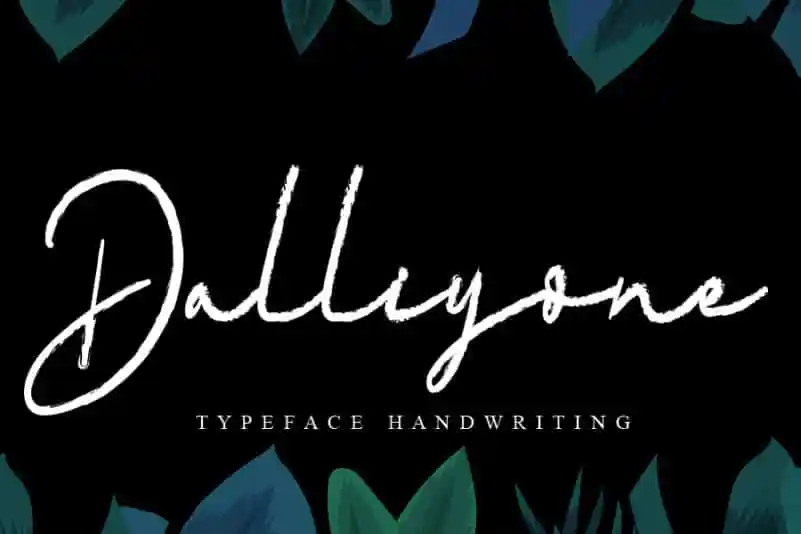
Dalliyone Script Font – Download Grátis
A Dalliyone Script Font é uma elegante escolha para quem busca adicionar personalidade aos seus projetos digitais. Este estilo de letra feito à mão com traços de pincel traz um toque único e autêntico, perfeito para transformar suas ideias criativas em verdadeiras obras de arte. Seja para o Instagram ou até mesmo na elaboração de pratos decorativos artesanais, essa fonte tem tudo o que você precisa para dar vida aos seus projetos. Ela oferece uma aposta segura tanto para quem busca um visual retrô e sofisticado quanto para aqueles que desejam algo mais audacioso e chamativo. Com a Dalliyone Script Font, qualquer projeto pode se transformar em uma verdadeira obra de arte feita à mão.